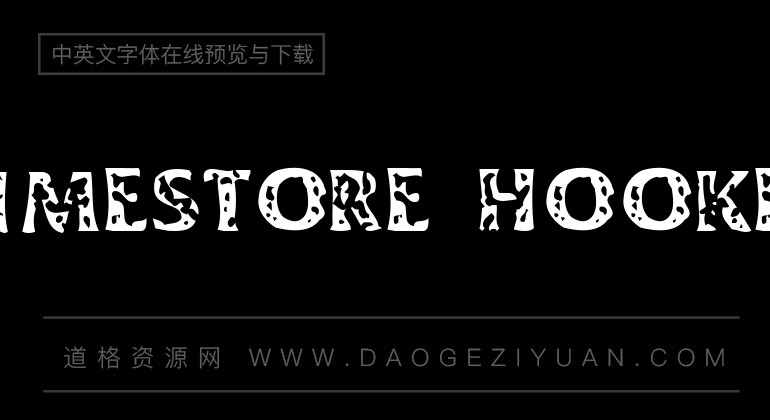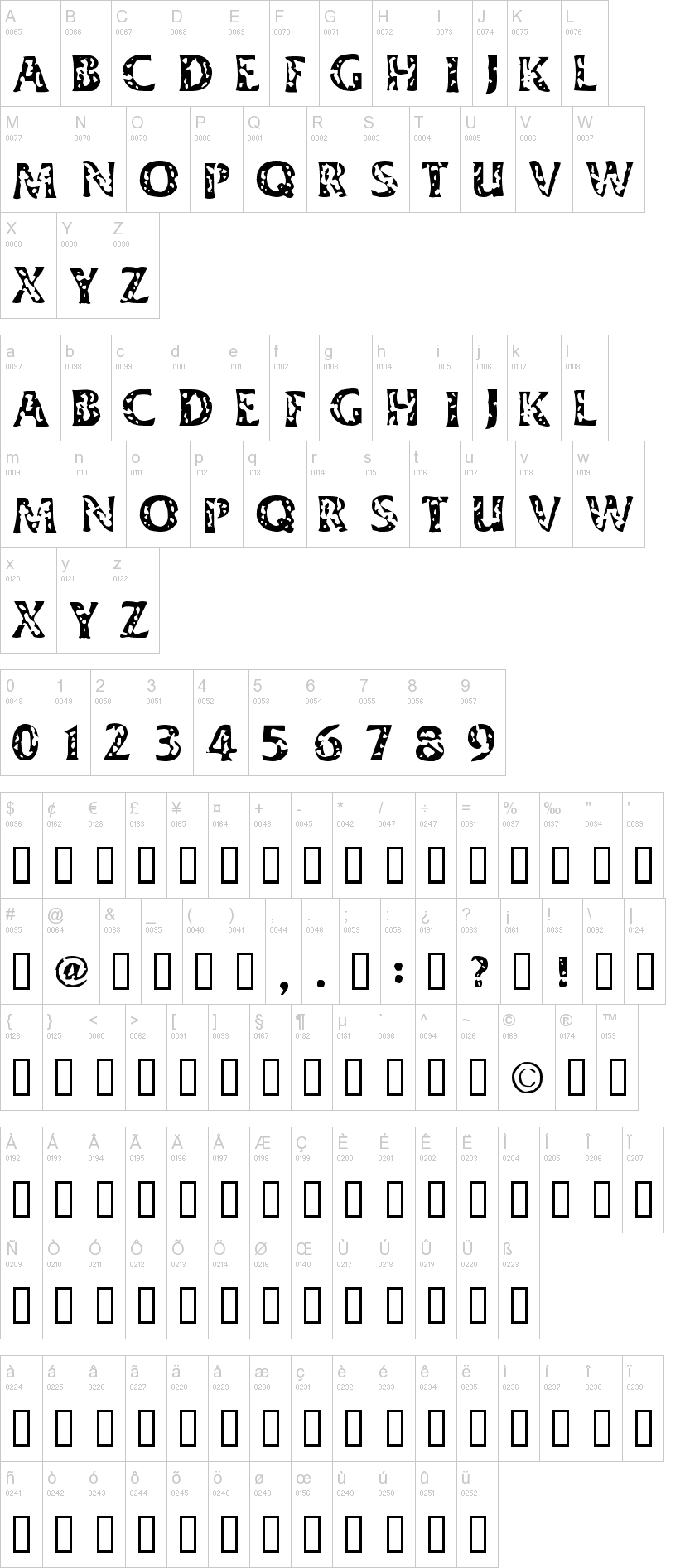
Dimestore Hooker
Dimestore Hooker 是一款特殊的手写字体,它的特点是有一种折行、折叠、折角的感觉,具有一种抽象的、折行的、折角的复古风格,可以给设计师提供更多的创意空间。它的字体特点就是折行,折角,折叠,可以创造出独特的视觉效果,更适合用于海报、广告、品牌标识、网页设计,也可以用于T恤、杂志封面、书籍封面等。
Dimestore Hooker是一款非常不错的手写艺术字体,具有很好的视觉感,适合于文化类的宣传设计、商业类品牌的广告和产品包装设计以及个性化文字排版等较多场景。